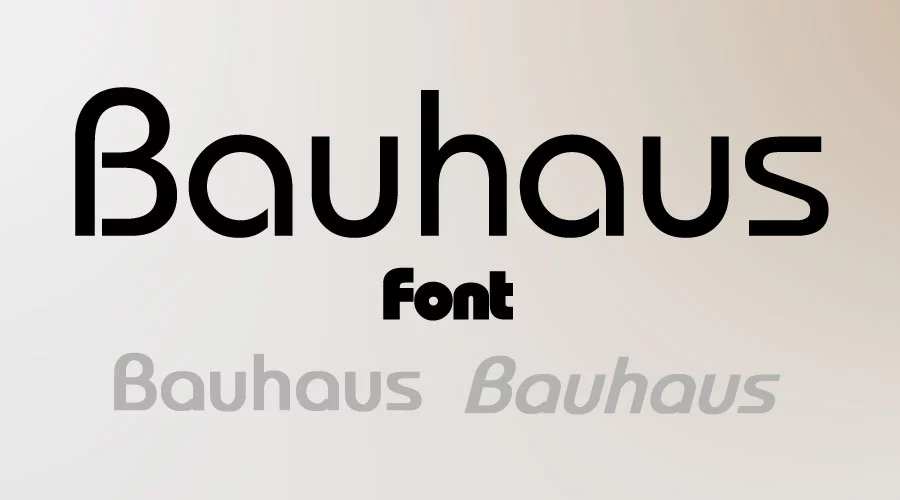
Font Bauhaus là một kiểu chữ mang đậm tinh thần của trường phái thiết kế Bauhaus. Đây là một phong trào nghệ thuật và thiết kế ra đời tại Đức vào đầu thế kỷ 20. Font này nổi bật với phong cách hình học tối giản, phản ánh triết lý “form follows function” (hình thức theo chức năng) một nguyên lý cốt lõi của trường phái Bauhaus.
Đặc điểm nổi bật của font Bauhaus
Hình học rõ ràng
Font Bauhaus được thiết kế dựa trên các hình học cơ bản như hình tròn, hình vuông và tam giác. Những yếu tố này tạo nên một cấu trúc chữ cái cực kỳ rõ ràng, cân đối và có tính đối xứng cao. Nhờ đó, font chữ mang lại cảm giác ổn định, chắc chắn nhưng không kém phần sáng tạo, rất dễ để thu hút ánh nhìn của người xem.
Không chân (Sans-serif)
Khác với các font serif truyền thống có chân chữ cong hoặc vuốt dài, font Bauhaus hoàn toàn không có chân (sans-serif). Điều này giúp cho kiểu chữ này trở nên hiện đại, tối giản và cực kỳ dễ đọc, nhất là khi hiển thị ở kích thước lớn trong tiêu đề hoặc thiết kế quảng cáo.
Tối giản
Tinh thần tối giản là một trong những yếu tố cốt lõi của trường phái Bauhaus. Font chữ cùng tên này cũng kế thừa triết lý đó với thiết kế gọn gàng, dứt khoát và không có bất kỳ chi tiết rườm rà nào. Chính sự đơn giản này lại là điểm mạnh giúp font Bauhaus trở nên linh hoạt trong nhiều hoàn cảnh sử dụng khác nhau.
Đậm chất cổ điển – hiện đại
Dù được ra đời từ đầu thế kỷ 20, nhưng Bauhaus vẫn giữ được sự thời thượng nhờ sự hòa quyện giữa chất retro cổ điển và tính hiện đại trong từng đường nét. Nó mang lại cảm giác vừa hoài niệm, vừa tân tiến – rất phù hợp với các thiết kế yêu cầu chiều sâu nghệ thuật.
Ứng dụng của font Bauhaus
Thiết kế poster, tiêu đề, bao bì mang phong cách retro
Font Bauhaus thường được sử dụng làm tiêu đề chính trong các poster quảng cáo, áp phích sự kiện hoặc bao bì sản phẩm. Nhờ vào hình khối rõ ràng và phong cách mạnh mẽ, font giúp thu hút sự chú ý ngay lập tức mà không cần sử dụng màu sắc quá nổi bật.
Logo và bộ nhận diện thương hiệu
Với vẻ ngoài tinh gọn, dễ nhận diện và mang dấu ấn nghệ thuật, font Bauhaus rất được ưa chuộng trong thiết kế logo. Đặc biệt, nó phù hợp với các thương hiệu mang định hướng sáng tạo, cá tính hoặc có liên quan đến lĩnh vực công nghệ, kiến trúc, nghệ thuật đương đại.
Sản phẩm truyền thông ngành thời trang, nội thất, kiến trúc
Trong các ấn phẩm truyền thông cao cấp như catalogue nội thất, lookbook thời trang hay ấn phẩm triển lãm kiến trúc, font Bauhaus được sử dụng để tạo ra phong cách sang trọng nhưng không cứng nhắc. Nó giúp tôn lên tinh thần thẩm mỹ đương đại, đậm dấu ấn cá nhân của thương hiệu.
Nếu bạn đang tìm một font chữ mang vẻ đẹp hiện đại, hình học, tối giản mà vẫn giữ được chiều sâu nghệ thuật thì font Bauhaus chính là lựa chọn đáng cân nhắc trong bất kỳ dự án thiết kế sáng tạo nào.